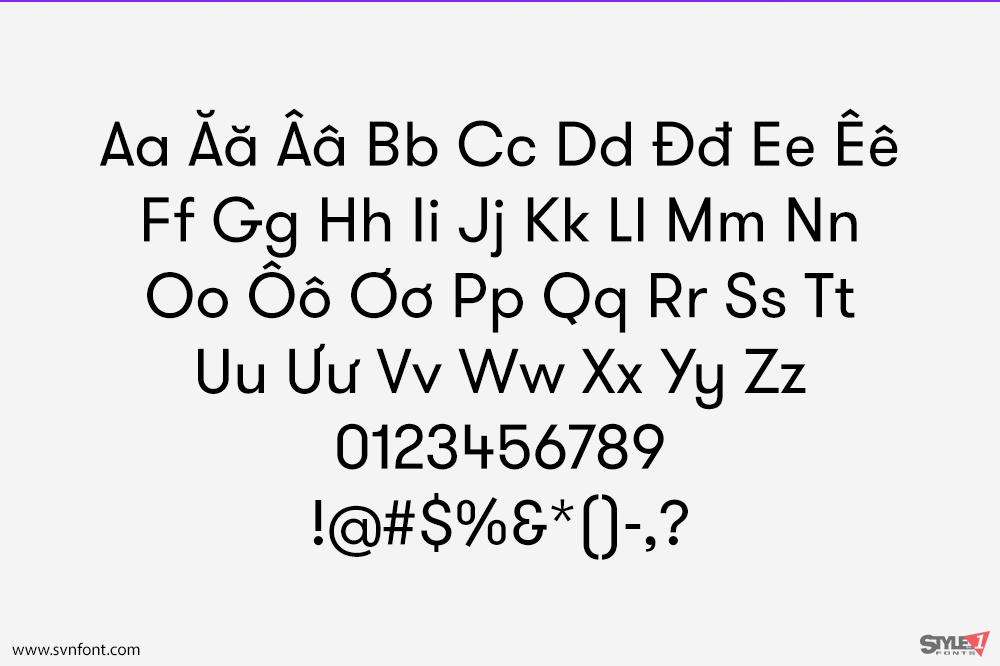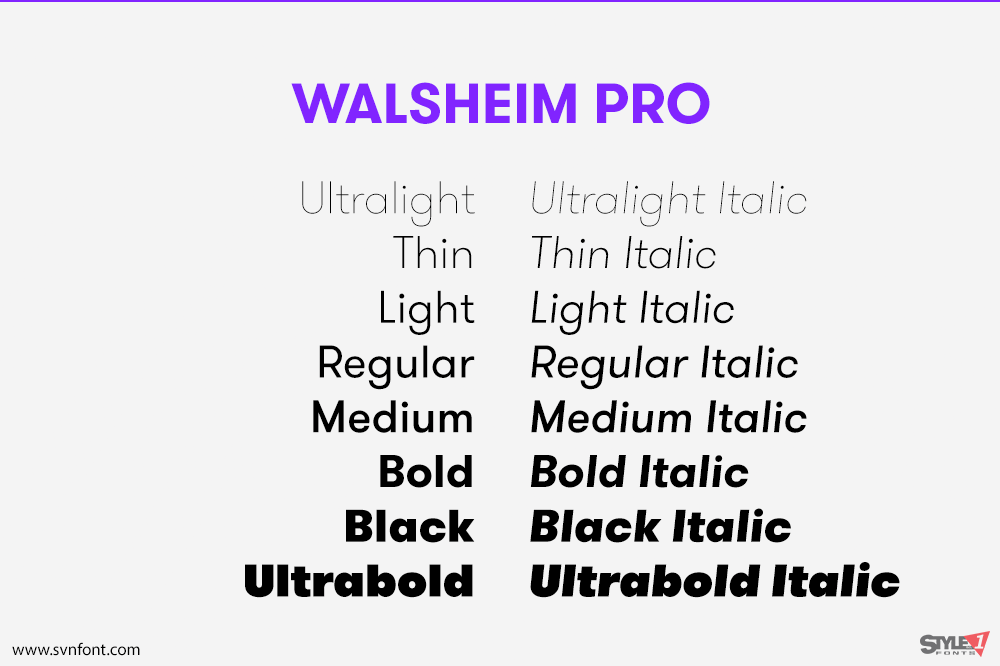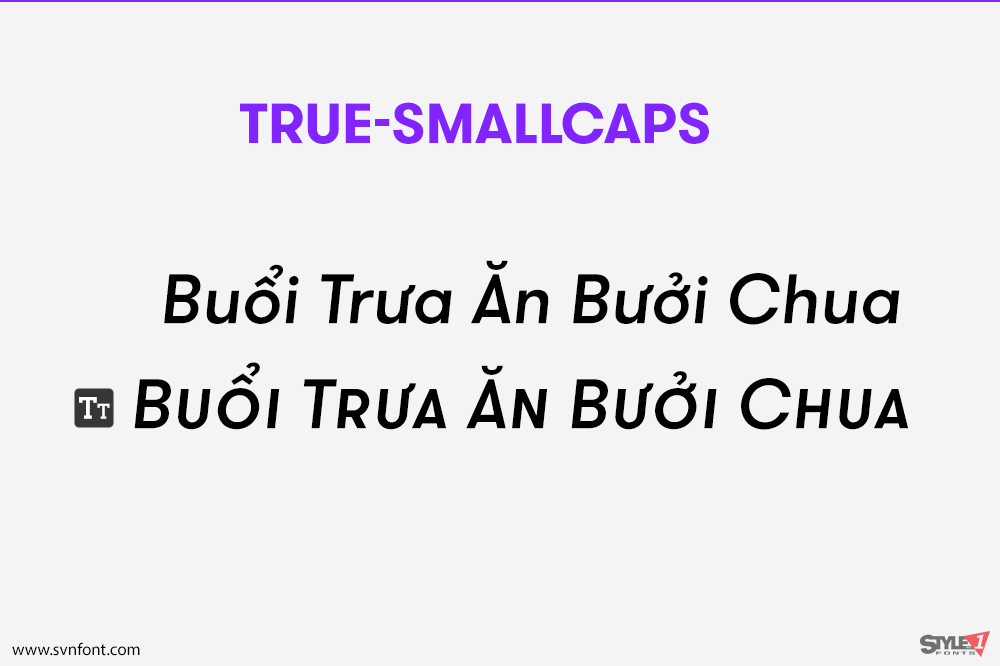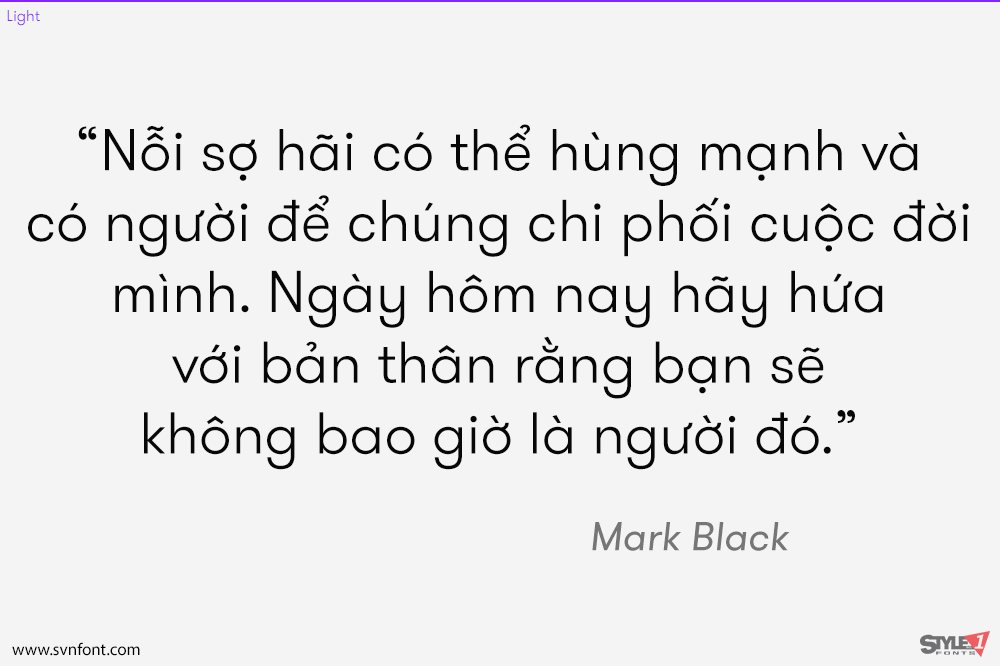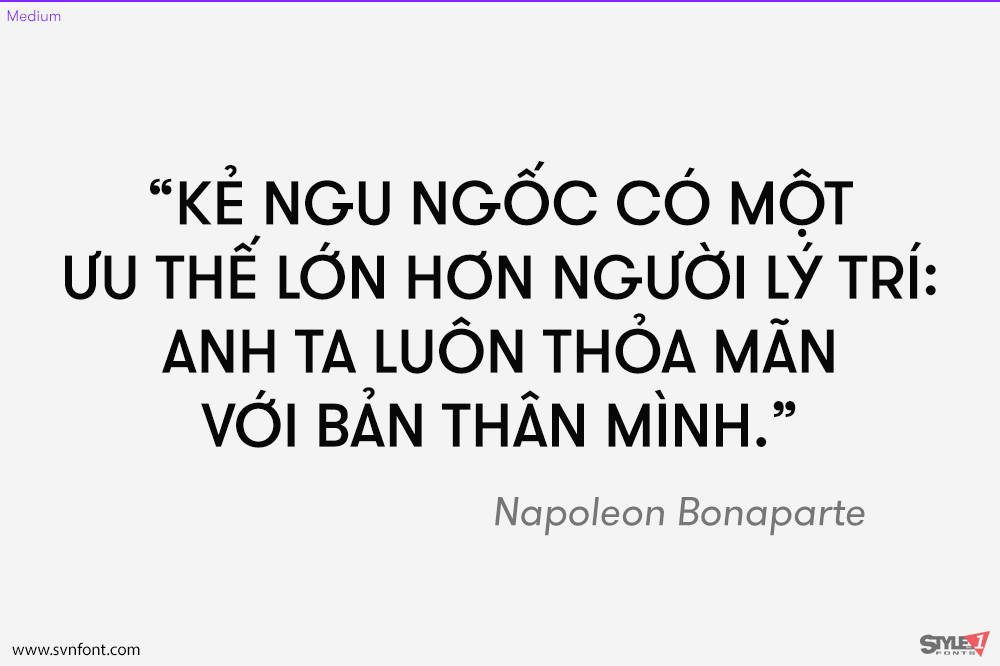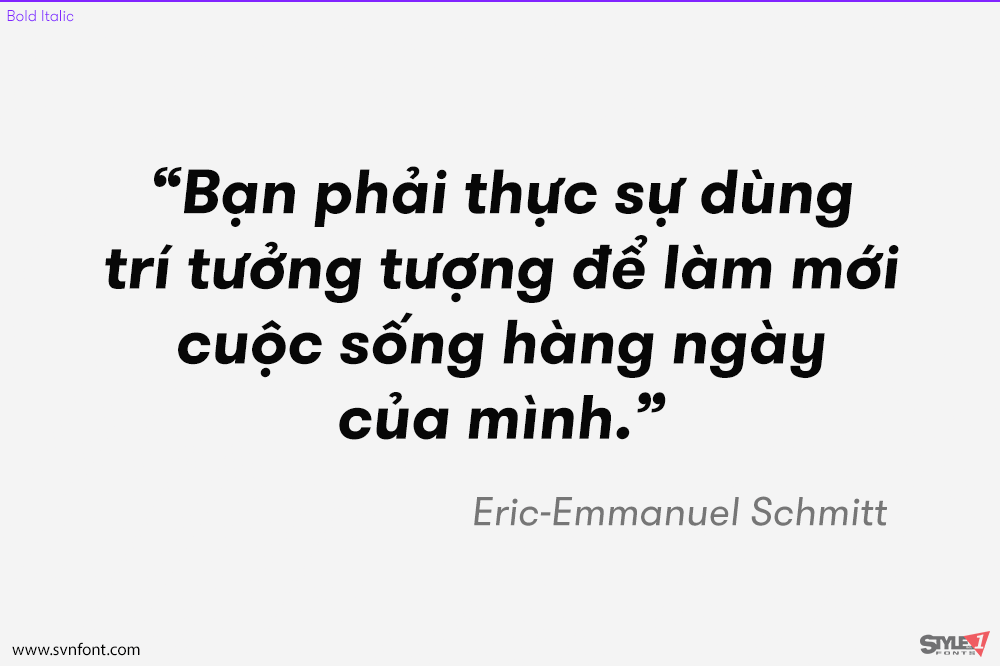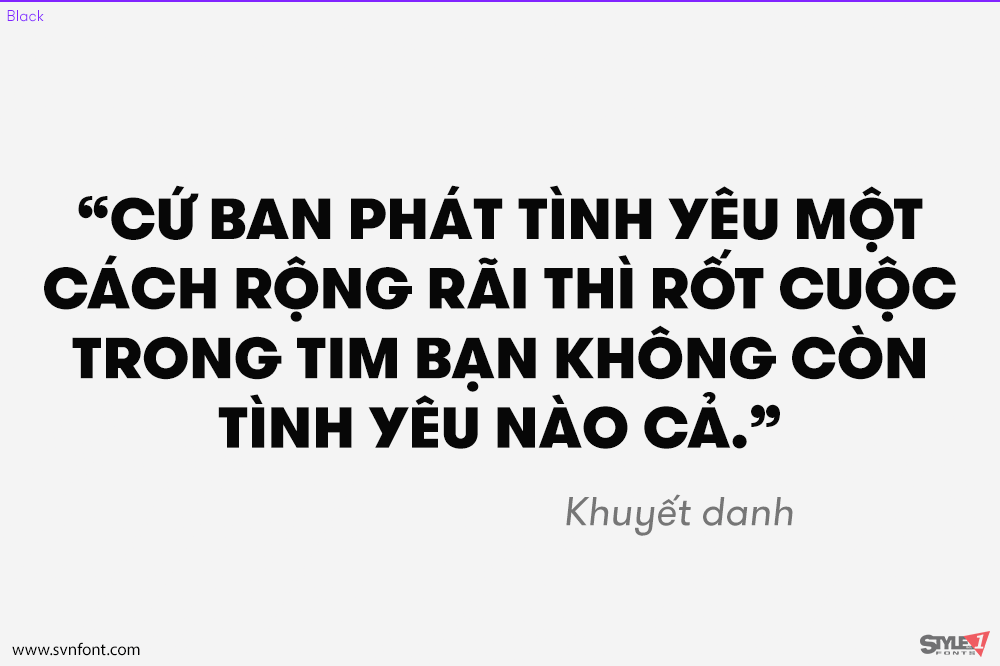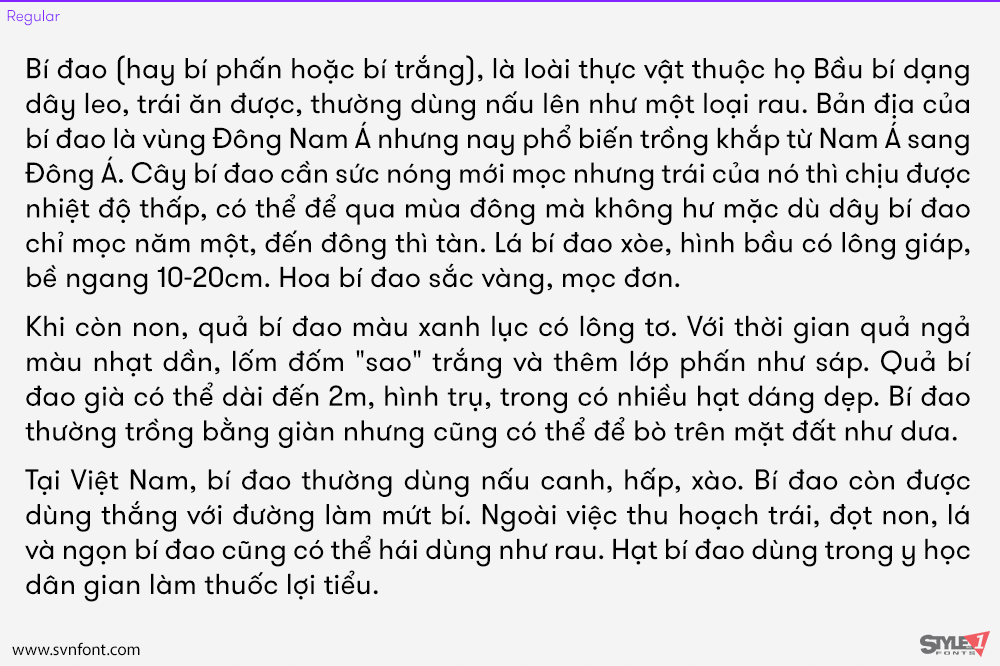
GT Walsheim là một kiểu chữ sans-serif hình học được thiết kế bởi Noël Leu và phát hành vào năm 2010 thông qua xưởng đúc Grilli Type của Thụy Sĩ. Thiết kế này lấy cảm hứng từ các chữ viết tay trên các tấm poster thập niên 1930 của nhà thiết kế người Thụy Sĩ Otto Baumberger. GT Walsheim có nhiều đặc điểm thú vị giúp nó nổi bật so với các phông sans hình học khác, chẳng hạn như thanh ngang ở chữ G viết hoa nhô ra ngoài. GT Walsheim có tám độ đậm—ultra light, thin, light, regular, medium, bold, black và ultra bold—mỗi độ đậm đều có kiểu nghiêng tương ứng.
Nhà thiết kế: Noël Leu
Nhà phát hành: Grill Type